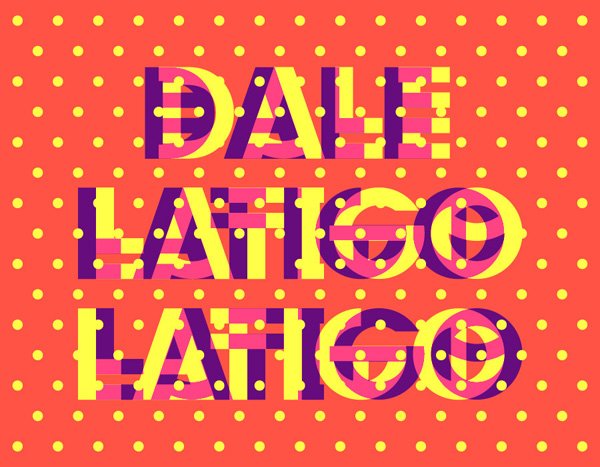
La tipografía caribeña Tanga Tanga
Esta tipografía se llama Tanga Tanga y es de Velckro Artwork. Tiene dos versiones de mayúscula para cada letra. Nada de minúsculas.
Para mostrarla, Velckro ha escrito seis frases escuchadas en canciones tropicales. “Papi, papi, papi, chulo”, “Ella se arrebata”, “Plátano maduro, plátano verde”, “Rabo de mono”, “Suelta como gabete” y “Dale, látigo, látigo”. Influencias de su cara B (el ilustrador se convierte en Don Fuegote los fines de semana y pincha reggaeton).